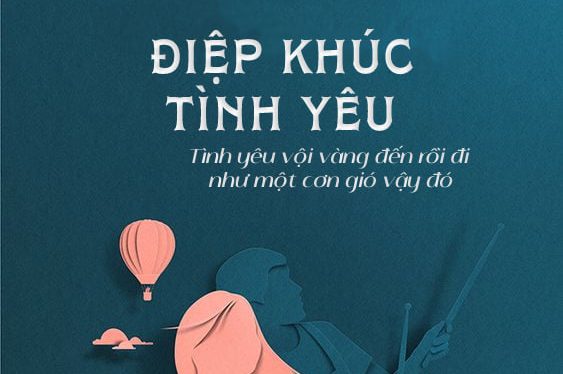
Giới thiệu về Font việt hoá MJ EFCOSongster-Pair
Trong thế giới sáng tạo, việc lựa chọn một Font Chữ phù hợp đóng vai trò then chốt giúp truyền tải thông điệp hiệu quả. Font việt hoá MJ EFCOSongster-Pair là bộ phông chữ độc đáo, mang phong cách hiện đại và thanh lịch. Đây là sự kết hợp hoàn hảo giữa nét cổ điển và xu hướng thiết kế mới, giúp các bạn học sinh và nhà trường dễ dàng tạo ra các ấn phẩm học tập bắt mắt. Việc sử dụng Font việt hoá MJ EFCOSongster-Pair không chỉ giúp văn bản dễ đọc mà còn tăng tính thẩm mỹ cao cho mọi loại tài liệu trực quan.
Đặc điểm nổi bật của bộ phông chữ MJ EFCOSongster
Bộ Font việt hoá MJ EFCOSongster-Pair được tối ưu hóa hoàn toàn cho bảng mã Unicode, giúp việc gõ tiếng Việt có dấu trở nên mượt mà và không xảy ra lỗi hiển thị. Phông chữ này sở hữu các đường nét uyển chuyển, tinh tế, rất thích hợp cho việc thiết kế tiêu đề bài giảng, thiệp mời sự kiện trường học hoặc các poster cổ động. Với cấu trúc ký tự rõ ràng, đây là lựa chọn hàng đầu cho những ai đang tìm kiếm sự khác biệt trong tư duy hình ảnh.
Ứng dụng Font việt hoá MJ EFCOSongster-Pair trong học tập
Các em học sinh có thể dùng Font việt hoá MJ EFCOSongster-Pair để làm slide thuyết trình thêm sinh động. Đối với giáo viên, phông chữ này hỗ trợ trình bày giáo án điện tử một cách chuyên nghiệp, thu hút sự chú ý của người học. Sự linh hoạt của bộ font cho phép ứng dụng từ in ấn cơ bản đến các định dạng kỹ thuật số phức tạp mà vẫn giữ được chất lượng hiển thị sắc nét.
Kết luận về bộ phông chữ